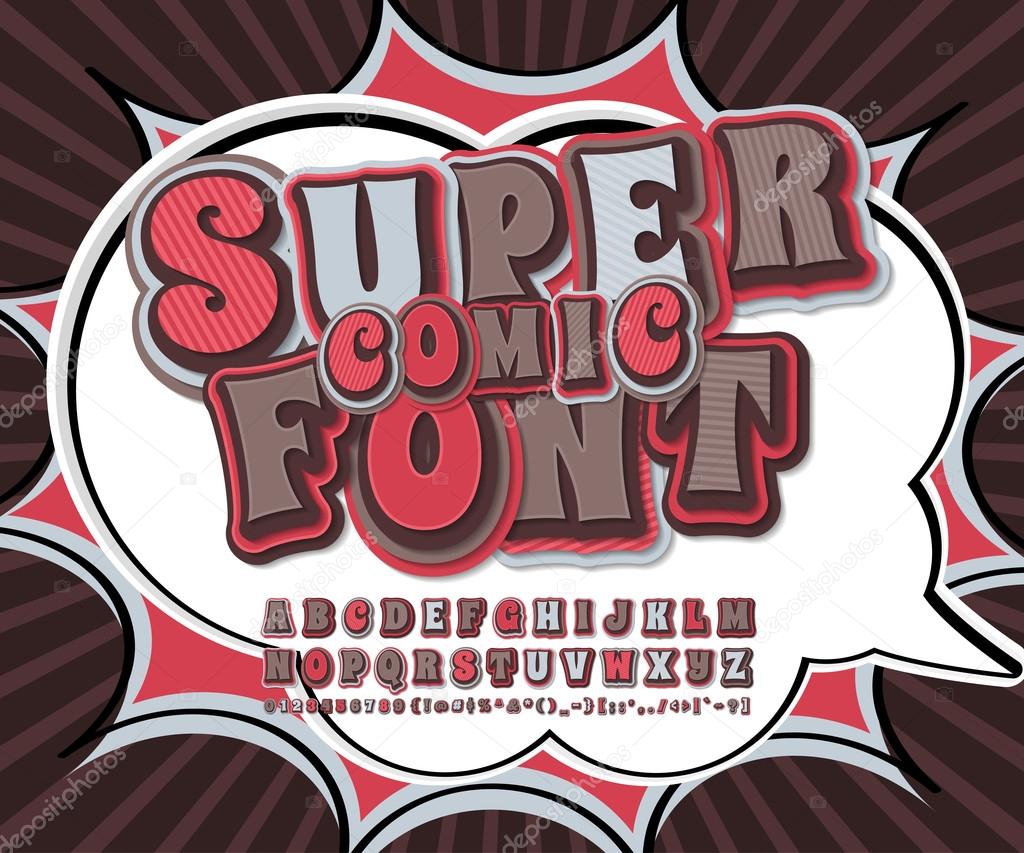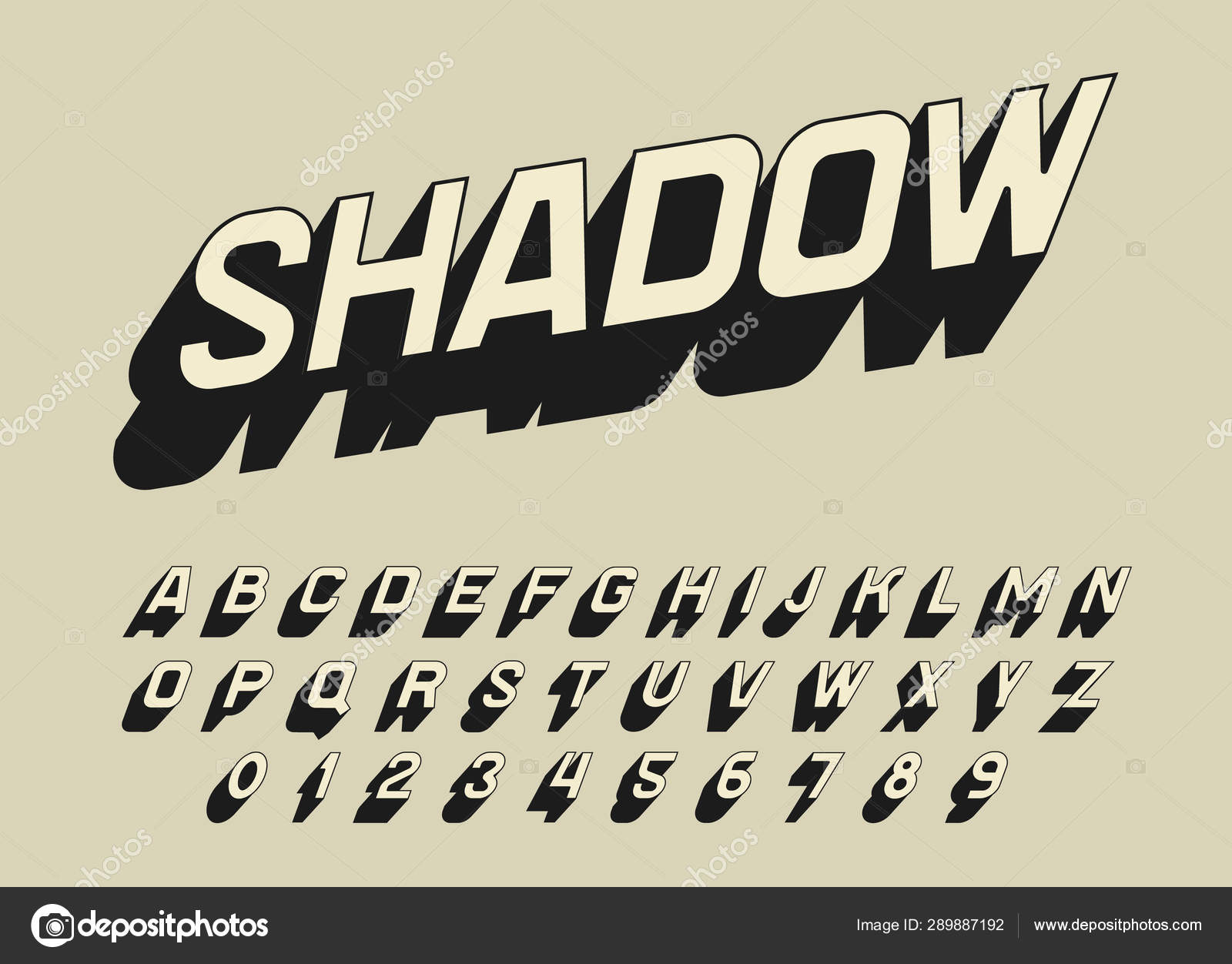
Стиль поп-арт в брендинге
Поп-арт или популярное искусство – это стиль в графическом дизайне, который зародился в 1950-1960 годах.
В те годы абстрактный импрессионизм стал заменяться новомодным популярным искусством, в основе которого были средства массовой информации и реклама.
Самым первым идолом поп-арта стала работа Ричарда Гамильтона и она называлась – «Что делает наши сегодняшние дома такими разными, такими привлекательными?»
Коллаж вызвал всеобщее удивление и ажиотаж, работа до сих пор считается основоположником стиля поп-арт.
Также одним из первых последователей популярного искусства становится Энди Уорхол. Однажды, в 1960 году он работал на компанию «Кока-кола» и создал для них новый дизайн бутылок. Эта работа произвела настоящий фурор, а Энди Уорхол становится популярным художником с неординарным мышлением и видением искусства.
Особенности стиля
Чтобы отличать стиль поп-арт от других стилей графического дизайна, можно выделить несколько особенностей популярного искусства. Например, в поп-арте всегда присутствуют яркие цвета. Это важно, ведь главной аудиторией является молодежь, которую привлекают яркие расцветки.
Композиционные решения в популярном искусстве всегда динамичные и неожиданные. А главными героями обычно становятся известные фигуры (певцы, актрисы, политики).
В поп-арте часто используется техника коллажа и китча. А также, стиль рисовки из комиксов. Жирные контуры, живые герои, которые вот-вот начнут двигаться, и техника растровых точек, словно при печати в типографии.
Вы, наверное, не раз замечали изображения Мэрилин Монро, раскрашенные и растиражированные в цветных квадратах. Это знаменитая работа в стиле поп-арт, сегодня по этому принципу оформляются фотографии других знаменитых людей. Открытые и простые цветовые решения, а также недорогие материалы, рассчитанные на массы.